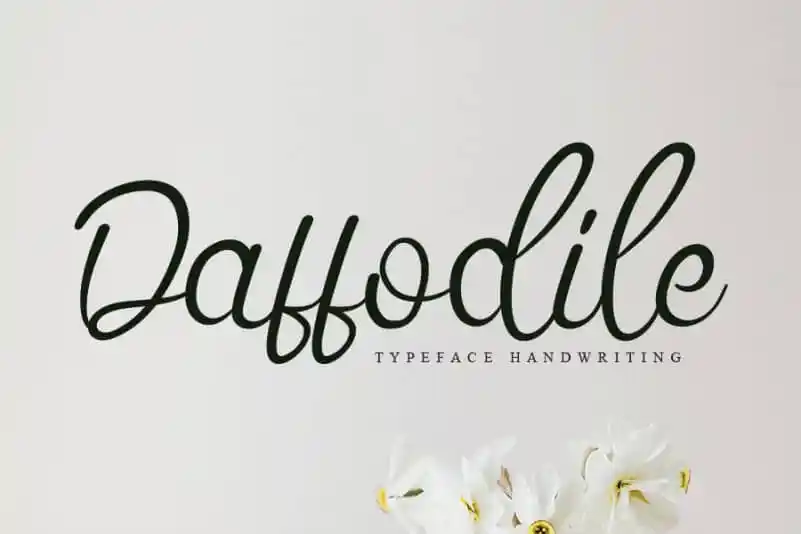
Daffodile Script Font é uma elegante e romântica fonte escrita a mão, perfeita para aquelas ocasiões especiais. Seu aspecto delicado e sofisticado faz dele um escolher natural para aplicações que exigem charme e refinamento, como cartas de casamento, selos personalizados, cartazes de boas-vindas, logotipos e até mesmo identidades corporativas. Suas letras perfeitamente humanizadas permitem uma utilização versátil, fazendo dele um recurso indispensável para designers que buscam dar seu trabalho um toque único e pessoal. Como designer profissional, você certamente se sentirá confortável alocando Daffodile Script Font nas suas maiores obras de arte digitais.